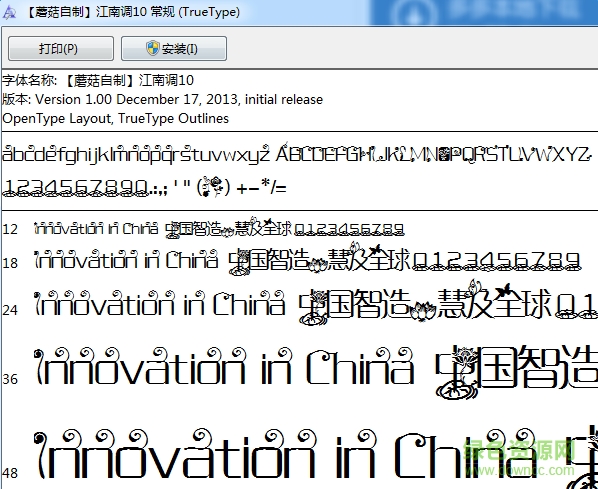
蘑菇自制江南調字體
江南調字體是網(wǎng)友蘑菇自制的一款非常炫酷的個性字體,你也可以稱之為蘑菇自制江南調10字體。該字體帶有蓮花圖案,線條粗細適中,字型簡潔大方得體,整體效果非常出色,并且字庫完整,可廣泛應用于平面設計、廣告設計、報紙雜志、正文標題等領域,喜歡的網(wǎng)友可免費下載收藏。
蘑菇自制江南調字體具有非常強的藝術氣息,超多花紋,給字體帶來生機,有一種別樣的感覺。歡迎來綠色資源網(wǎng)下載使用!